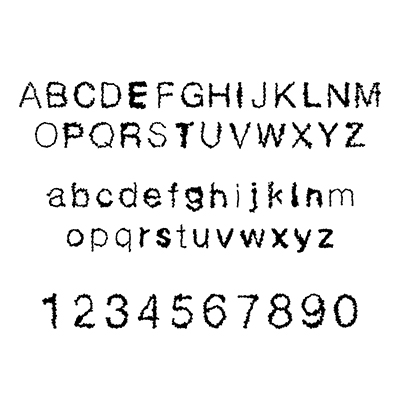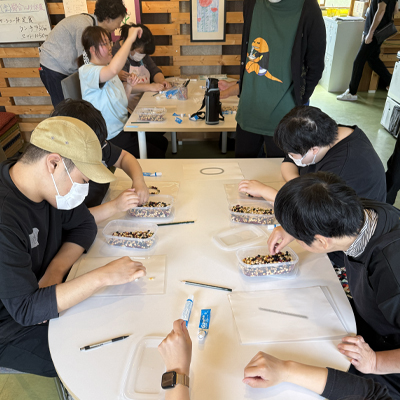
BEAN`S LIFE ふぉんと
豆から命が生まれるようにみんなでつくった言葉の豆。
Artistチームfuwarika
Designer山口久美子
Organization特定非営利活動法人b-らいふ
細かい作業だったけど楽しかったです。(チームfuwarika)
豆から芽が出て命が育つように、このフォントからもいろいろな言葉が生まれていきます。豆の「BEAN`S」とb-らいふの「b」をかけ合わせたフォントです。(山口久美子)
普段、Fuwaricaのメンバーが一同に会する事がないので、皆で一つのことに取り組む貴重な機会になりました。同じ題材に取り組んでいても、それぞれの個性がしっかり出るものなんですね。(特定非営利活動法人b-らいふ)